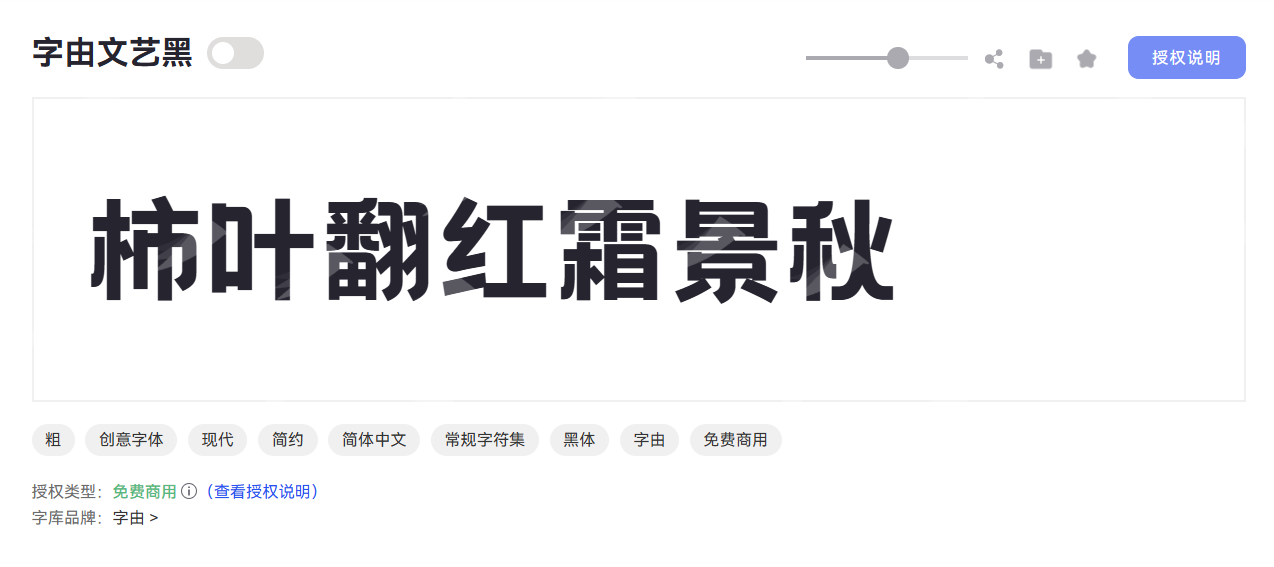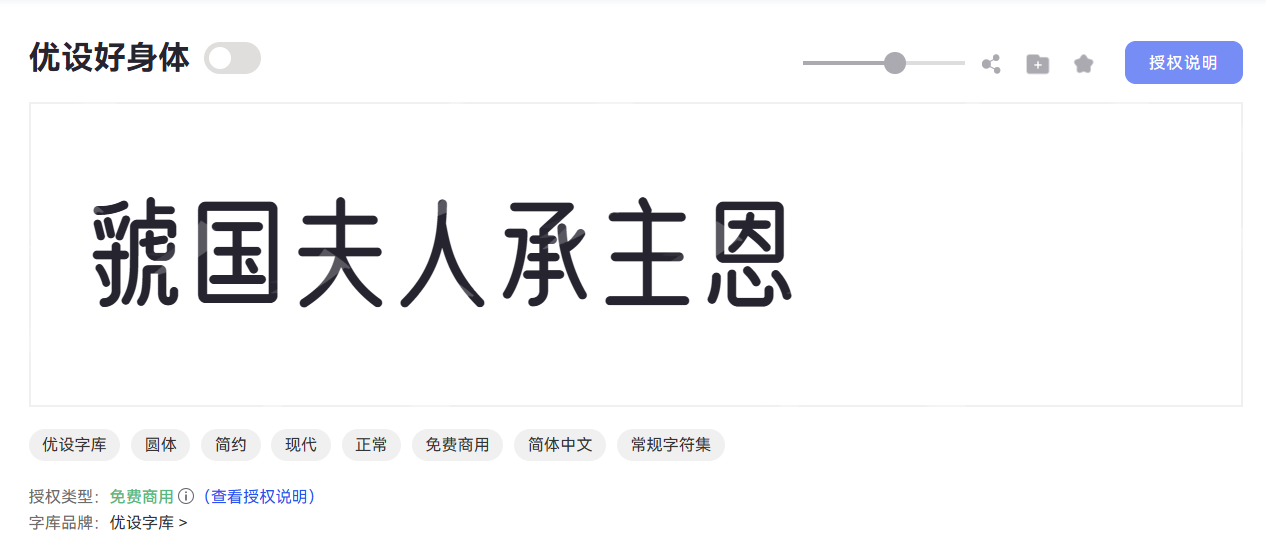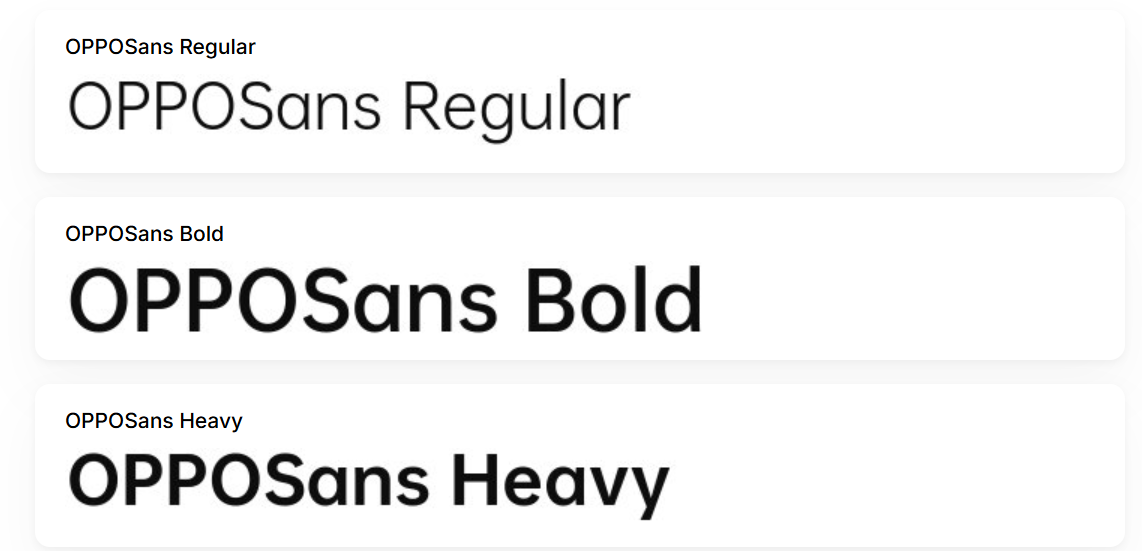
适合咖啡行业的字体怎么选?品牌字体使用实用指南
在进行品牌设计时,字体不仅承担信息传递的作用,也会影响消费者对品牌气质的感知。从咖啡店菜单、包装设计、宣传海报,到社交媒体内容展示,不同风格的字体能够呈现出不同的品牌印象。而选择一款适合咖啡行业的字体,需要综合考虑品牌定位、使用场景以及商业授权问题。下面本文结合咖啡行业的常见设计场景,整理出 7 款适合咖啡行业的字体,一起来了解吧!
一、适合咖啡行业的字体推荐:
1、字由文艺黑
字由文艺黑的整体风格简洁自然,带有一定的人文气息。在咖啡品牌设计中,字体需要传递舒适、放松的消费体验,而字由文艺黑较为柔和的视觉特点,可以很好地应用在咖啡店招牌、菜单标题、产品包装以及宣传海报中。
在实际使用过程中,这类字体比较适合强调品牌调性的设计。它能够减少商业设计中的距离感,让品牌形象更加贴近日常生活。该款字体也是专业字体网站【字由】的招牌字体之一,如果想要使用的话,可以前往访问字由官网了解。
2、优设好身体
优设好身体字体结构清晰,视觉表现较为轻松,比较适合用于年轻化咖啡品牌的设计场景,例如更注重空间体验和社交的咖啡店。在字体造型上,优设好身体不仅具有一定设计感,而且能保持良好的阅读体验,适合用于咖啡菜单标题、活动宣传、品牌标语等内容。在实际的应用场景中,我们还可以将它搭配插画、手绘元素或简约摄影图片一起来使用。
3、OPPO Sans
OPPO Sans是一款现代感较强的字体,它注重简洁和阅读体验,适合用于咖啡品牌的小程序或独立 APP 的内容展示。为咖啡品牌进行内容宣传、活动说明以及线上页面文字使用,尤其适合强调简约风格的咖啡品牌。
4、阿里妈妈刀隶体
部分咖啡品牌会结合东方文化、地域特色或手工咖啡理念打造品牌形象,这类场景就需要字体具有一定的故事感。而阿里妈妈刀隶体具有较明显的手写与传统书法特点,十分适合用于这类具有主题特色的咖啡品牌设计。但是由于这类字体风格较为突出,在实际使用时建议控制应用范围,并与简洁字体搭配使用,从而保持整体画面的协调性。
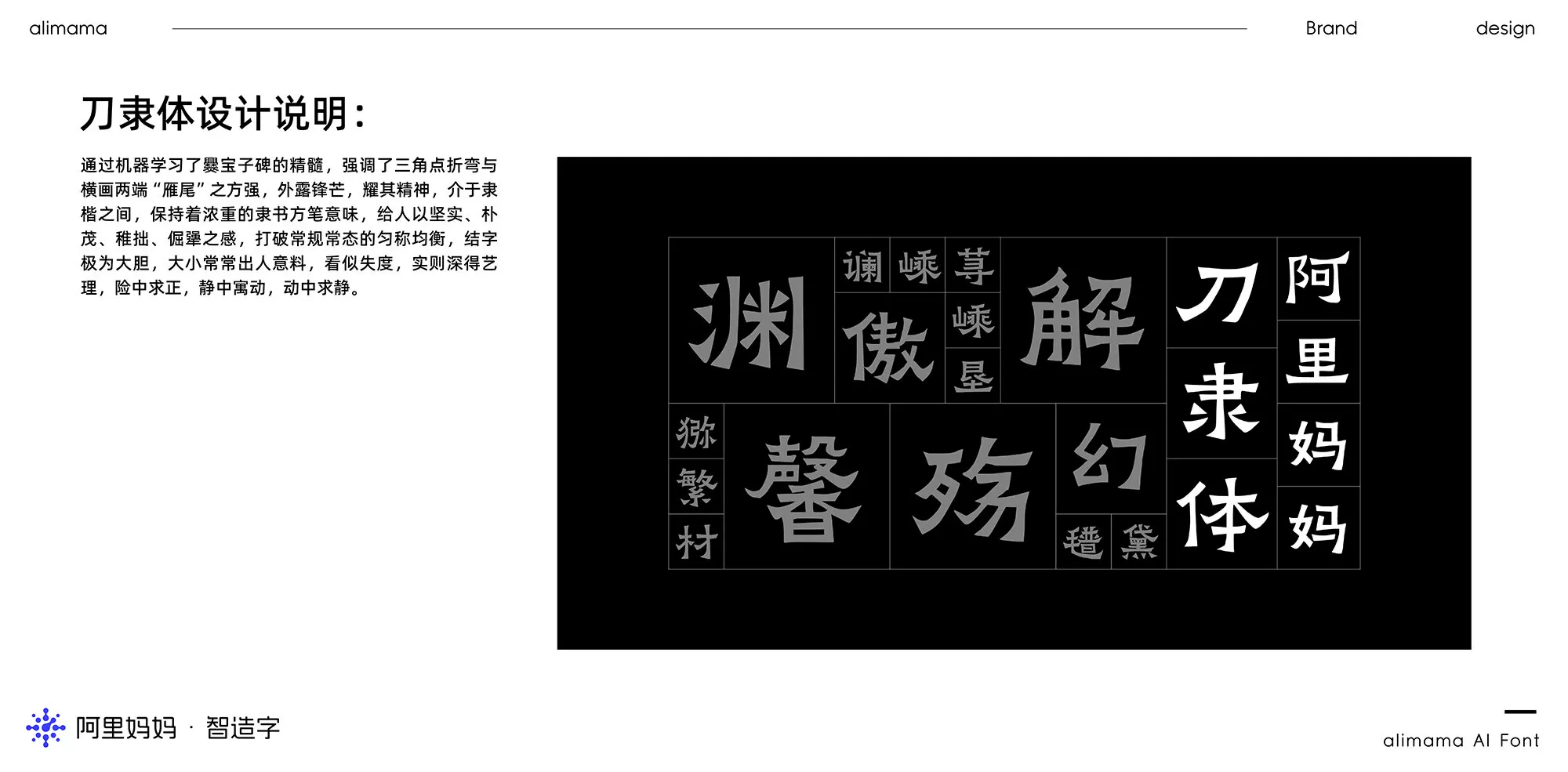
5、得意黑
随着咖啡消费场景不断丰富,越来越多品牌开始关注社交传播和视觉内容设计。得意黑这样一款具有现代设计感的字体,字体造型简洁,同时带有一定的个性化特点,就十分适合用于年轻化咖啡品牌了。
在咖啡新品推广、活动海报、品牌周边以及线上宣传内容中,得意黑能为你的咖啡品牌增强设计的辨识度。
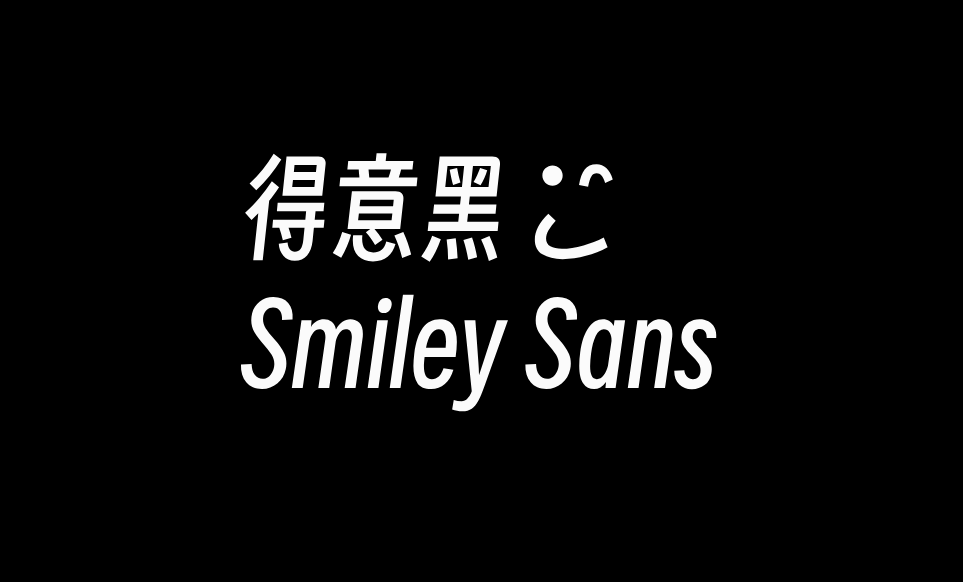
6、 未来荧黑
未来荧黑是一款偏现代风格的字体,同时带有一定科技感和年轻感。当一些咖啡品牌要结合数字化体验、潮流空间和年轻消费场景打造品牌形象时,就十分需要未来荧黑这样更偏向现代的字体设计了。我们可以把它应用于咖啡菜单、电子屏展示、线上活动页面以及品牌宣传图片中。
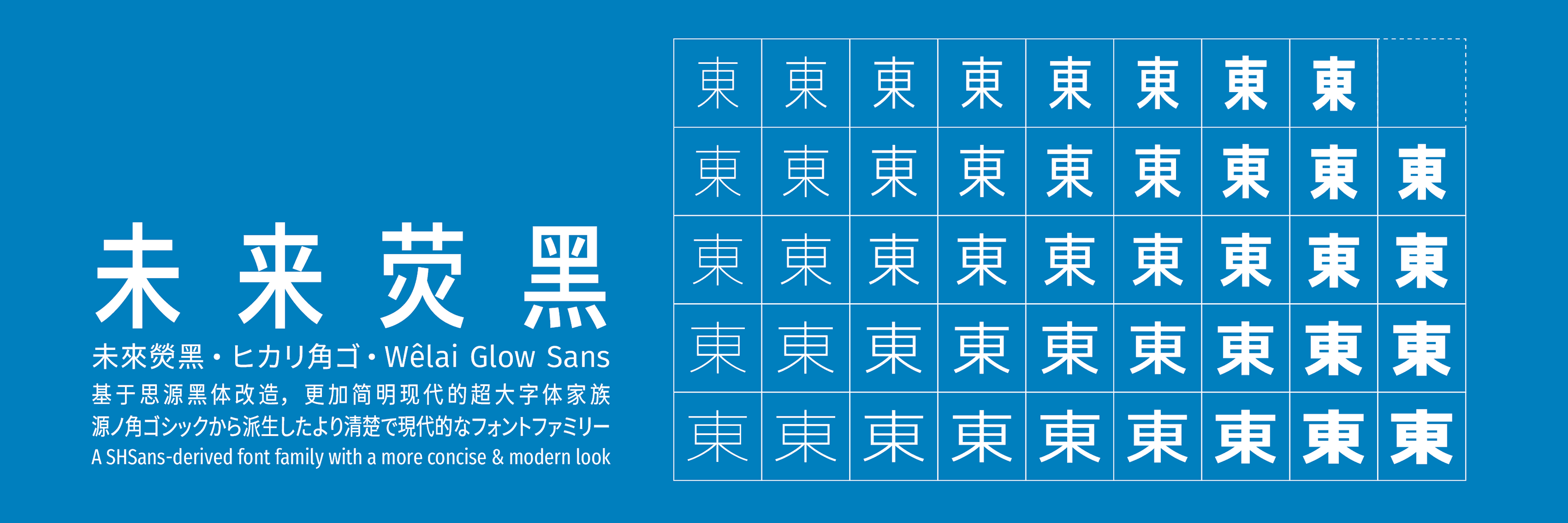
7、龙藏体
咖啡行业中,部分品牌希望突出手作理念、社区氛围或慢生活体验,因此会选择更具人情味的字体表达品牌特色,比如龙藏体。龙藏体是一款具有手写特色的字体,字体风格自然,能够带来更加亲切的视觉感受,对于要具有温度感的咖啡品牌设计来说再适合不过。
而为了进一步提升店内的生活气息,在实际使用时,我们还可以将这款字体与咖啡摄影图片、插画元素结合起来。